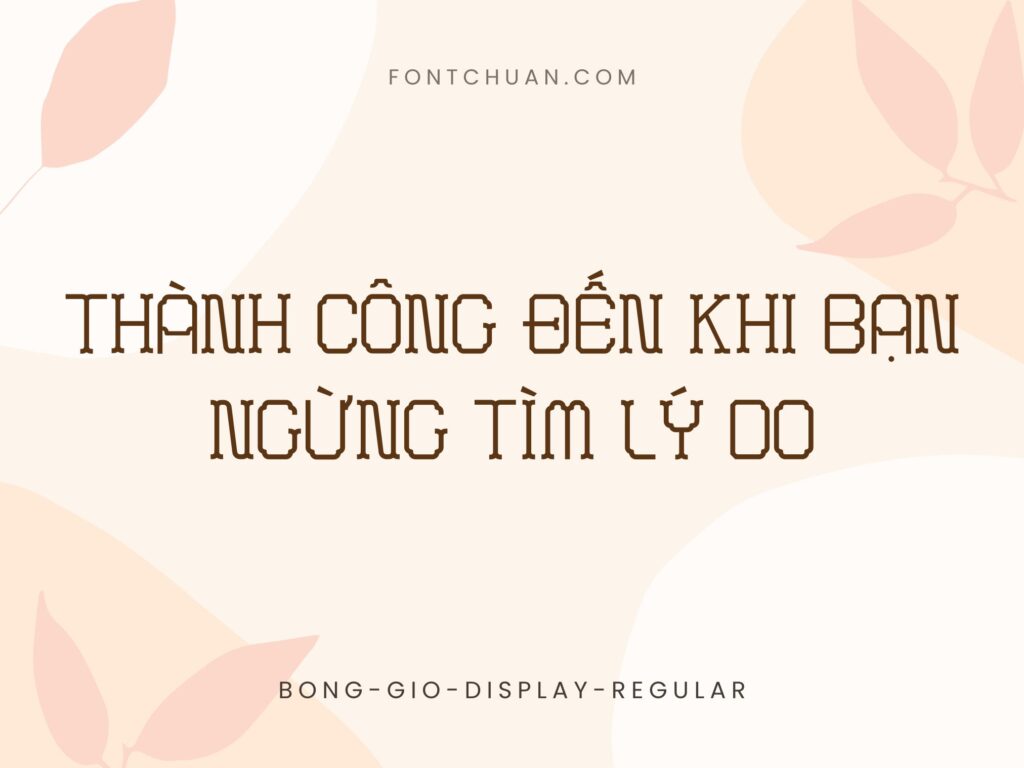
Font Bong Gio Display Việt Hóa
Tác giả Font: Vũ Phạm
Việt hóa bởi: Vũ Phạm
Bong Gio Display là một phông chữ trang trí, lấy cảm hứng từ hoa văn gạch bông gió phổ biến ở Sài Gòn trong thời kỳ Pháp thuộc. Loại gạch này được áp dụng trong nhiều công trình kiến trúc Việt Nam như tường, sàn và hàng rào với các họa tiết đối xứng và cổ điển. Phông chữ này được thiết kế bởi Vũ Phạm, nhằm tái hiện và giới thiệu lại nét văn hóa xưa của Sài Gòn, mang đến phong cách cổ điển và truyền thống. Bong Gio Display miễn phí cho cả mục đích sử dụng cá nhân và thương mại, giúp người dùng linh hoạt trong việc áp dụng vào các dự án khác nhau.
Với thiết kế độc đáo và mang đậm nét văn hóa, Bong Gio Display cũng có thể được sử dụng như một Font chữ thiệp cưới, tạo ra những tấm thiệp cưới mang phong cách cổ điển, trang nhã và tinh tế, đồng thời vẫn giữ được sự sáng tạo và điểm nhấn riêng cho từng thiết kế.